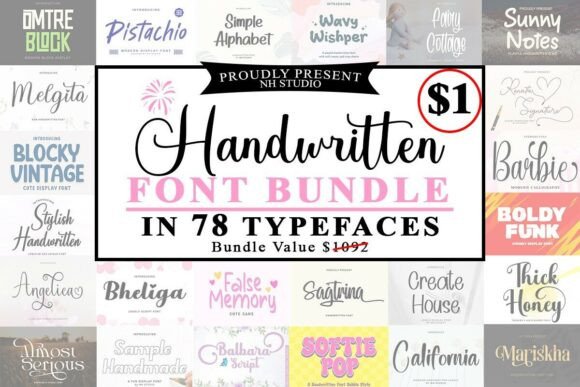
Handwritten Font Bundle
Trouver les bons éléments de conception peut être un défi, mais Handwritten Font Bundle propose une collection exceptionnelle qui rehausse instantanément votre travail.
Que vous créiez des produits POD (impression à la demande), des invitations de mariage ou des visuels pour les réseaux sociaux, Handwritten Font Bundle est un choix idéal.